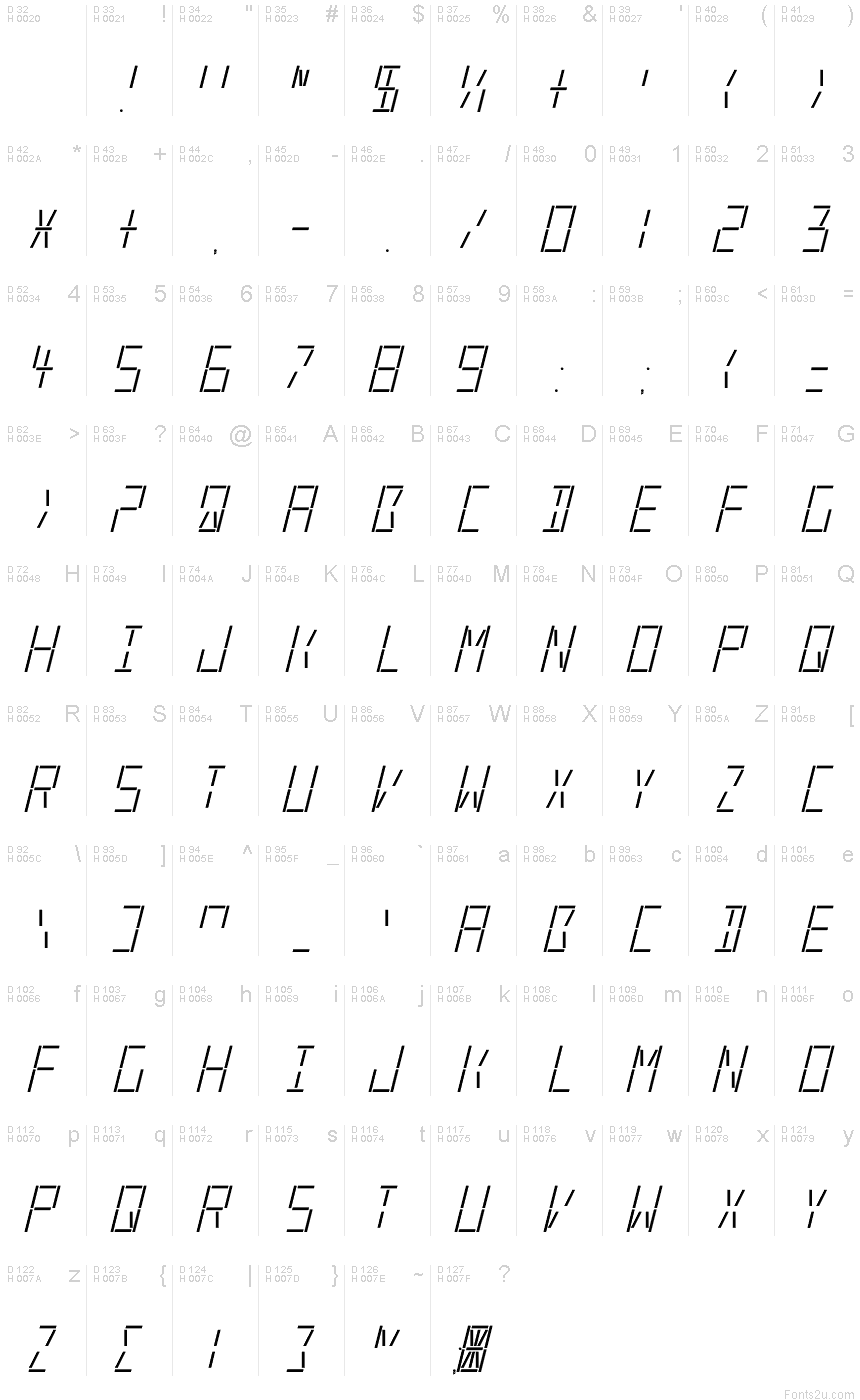
LED Real Italic autorstwa Matthew Welcha to darmowy, cyfrowy font wyświetlaczowy w kursywie, wyróżniający się wąskimi, segmentowanymi literami i pochyloną konstrukcją w stylu LED. Każdy znak zbudowany jest z ostrych, liniowych elementów z przyciętymi narożnikami i delikatnymi przerwami, co nadaje całości rytm ekranowego wyświetlacza przy zachowaniu czytelnej struktury.
LED Real Italic świetnie sprawdza się w tytułach gier arcade, etykietach technologicznych, ulotkach eventowych, menu w klimacie sci-fi czy grafikach tablic wyników, gdzie jej kanciaste segmenty dodają krótkim tekstom elektronicznego pulsu. Ten darmowy font pasuje również do akcentów na plakatach i w oznakowaniu cyfrowym, gdy potrzebujesz kompaktowego kroju displayowego, który wygląda jak wyjęty z panelu sterowania lub timera.